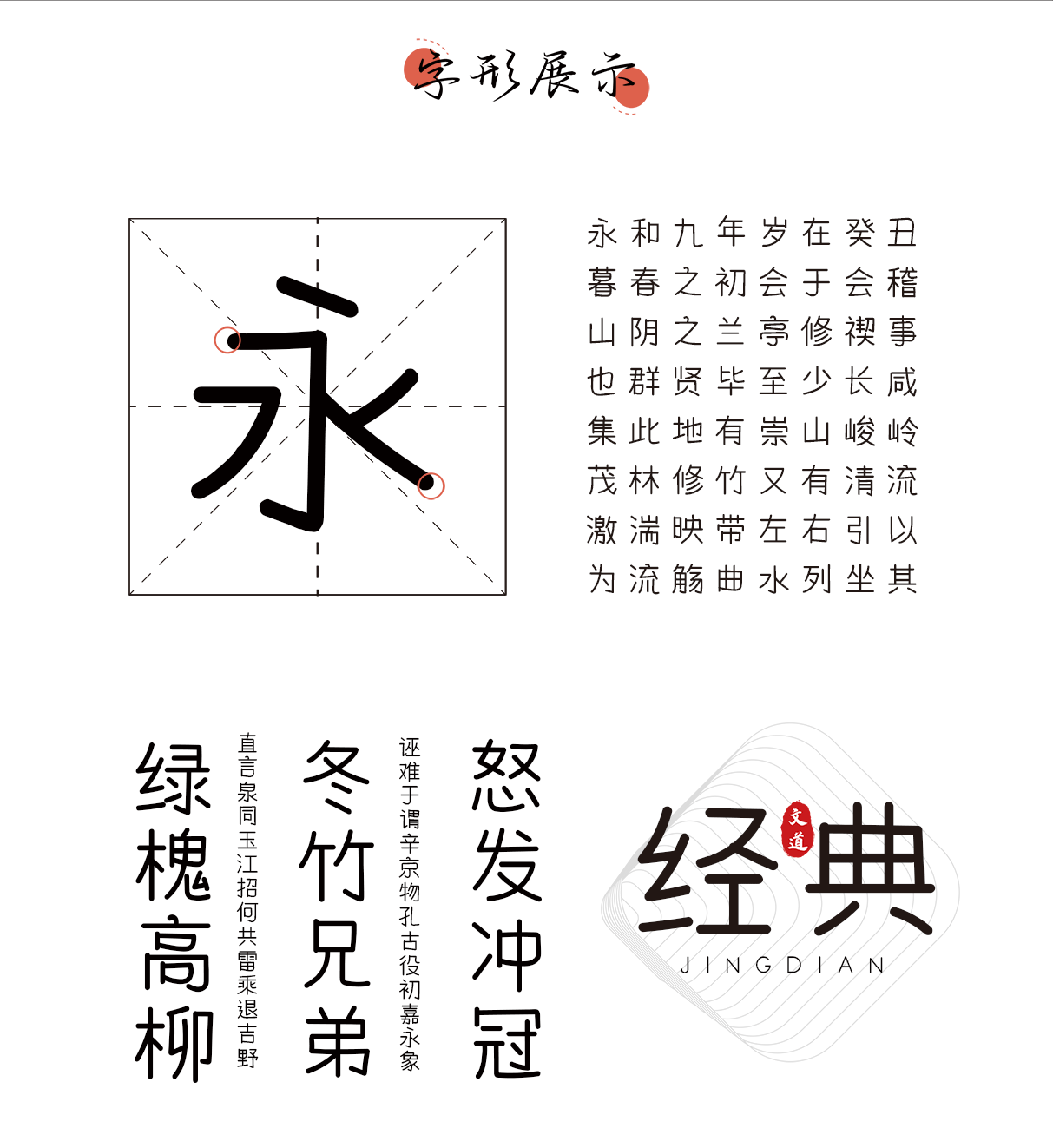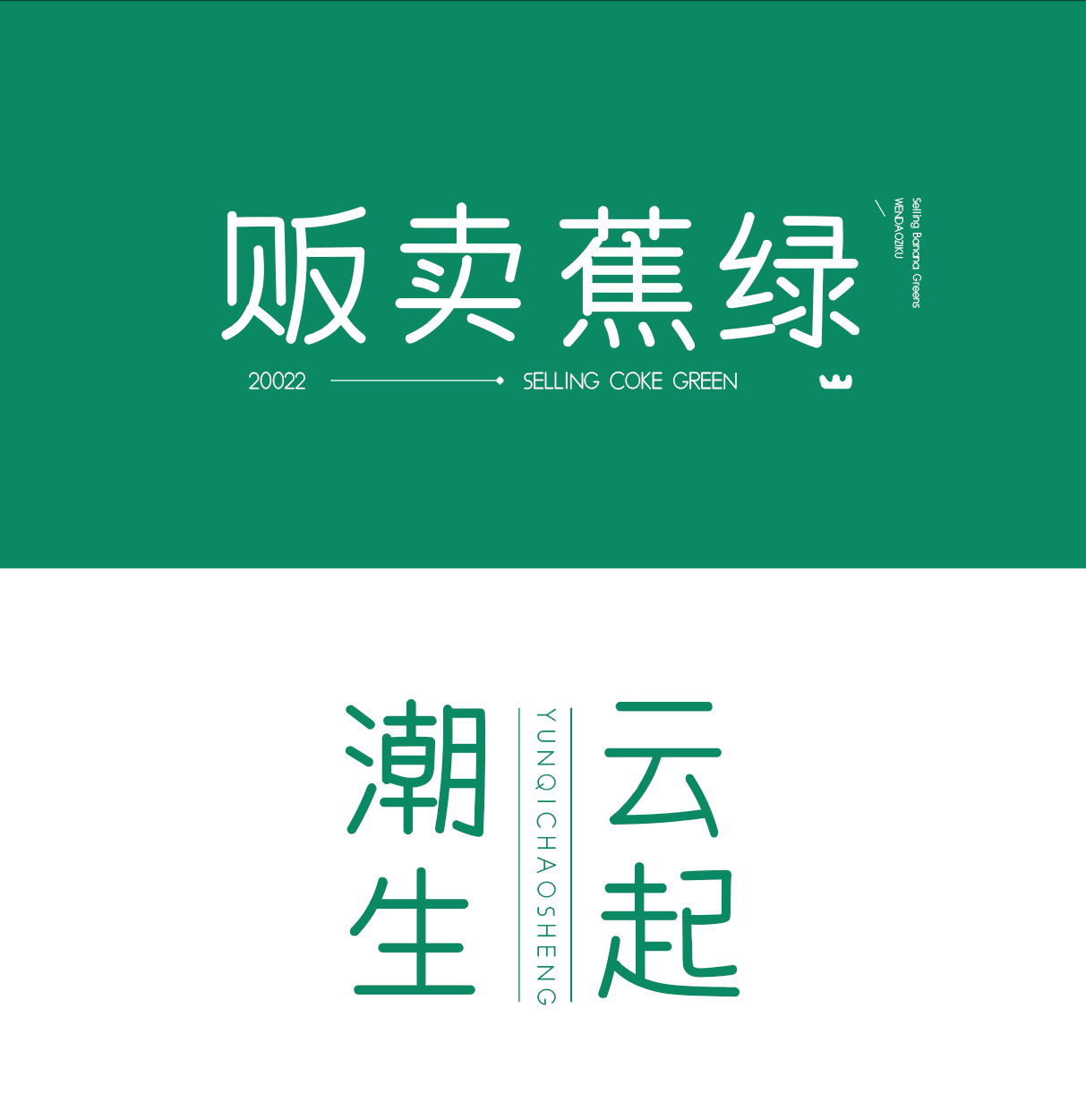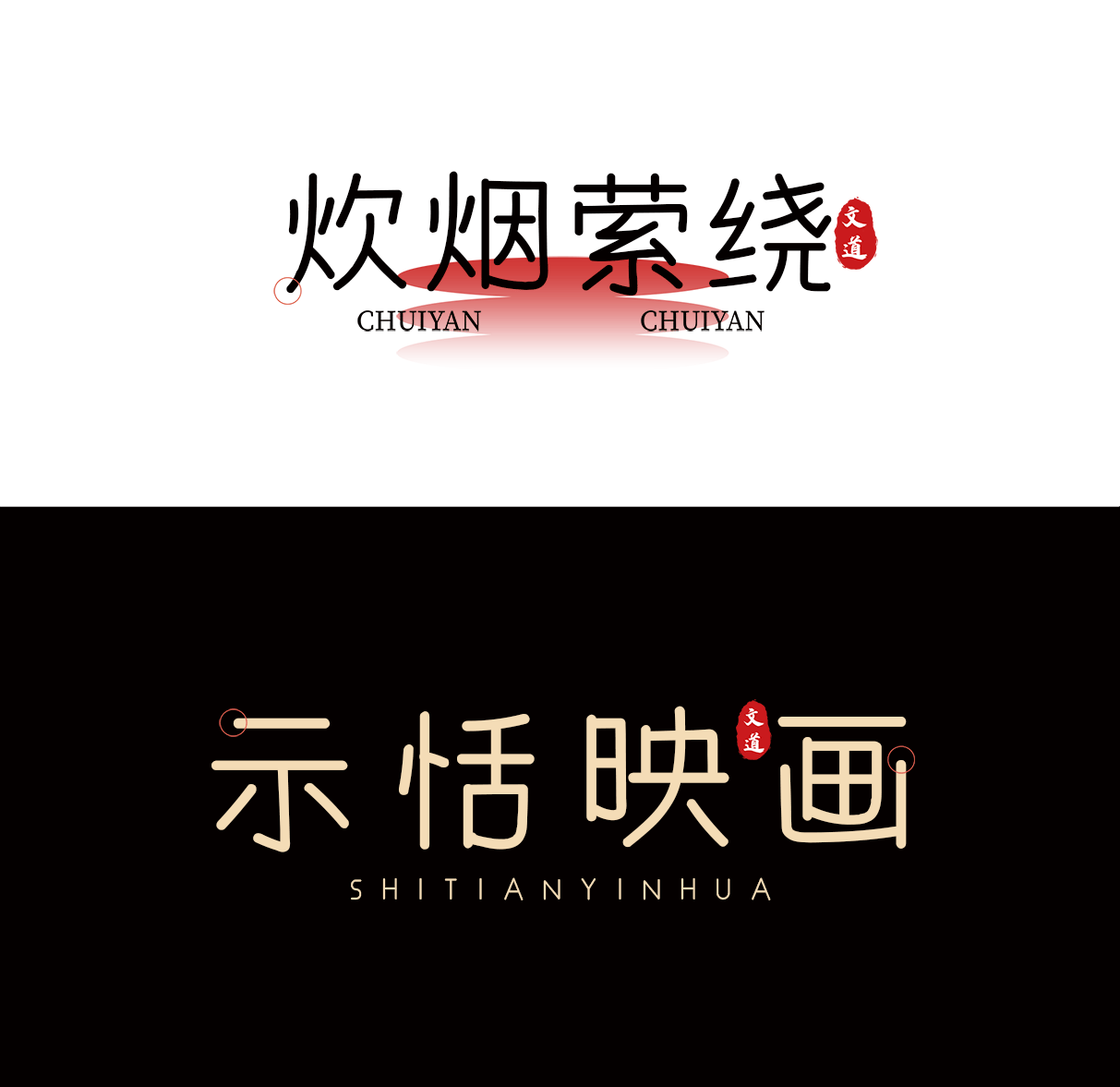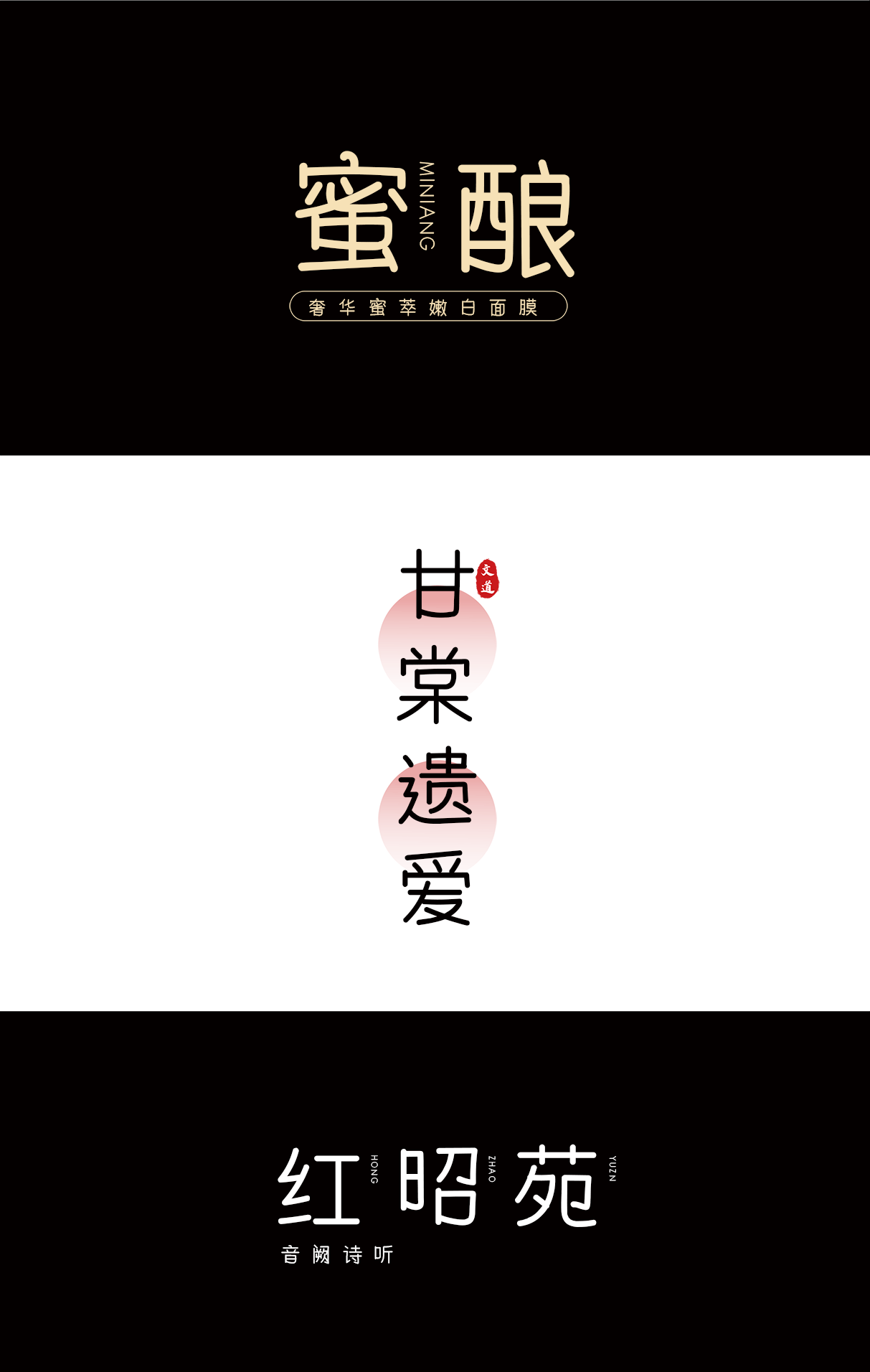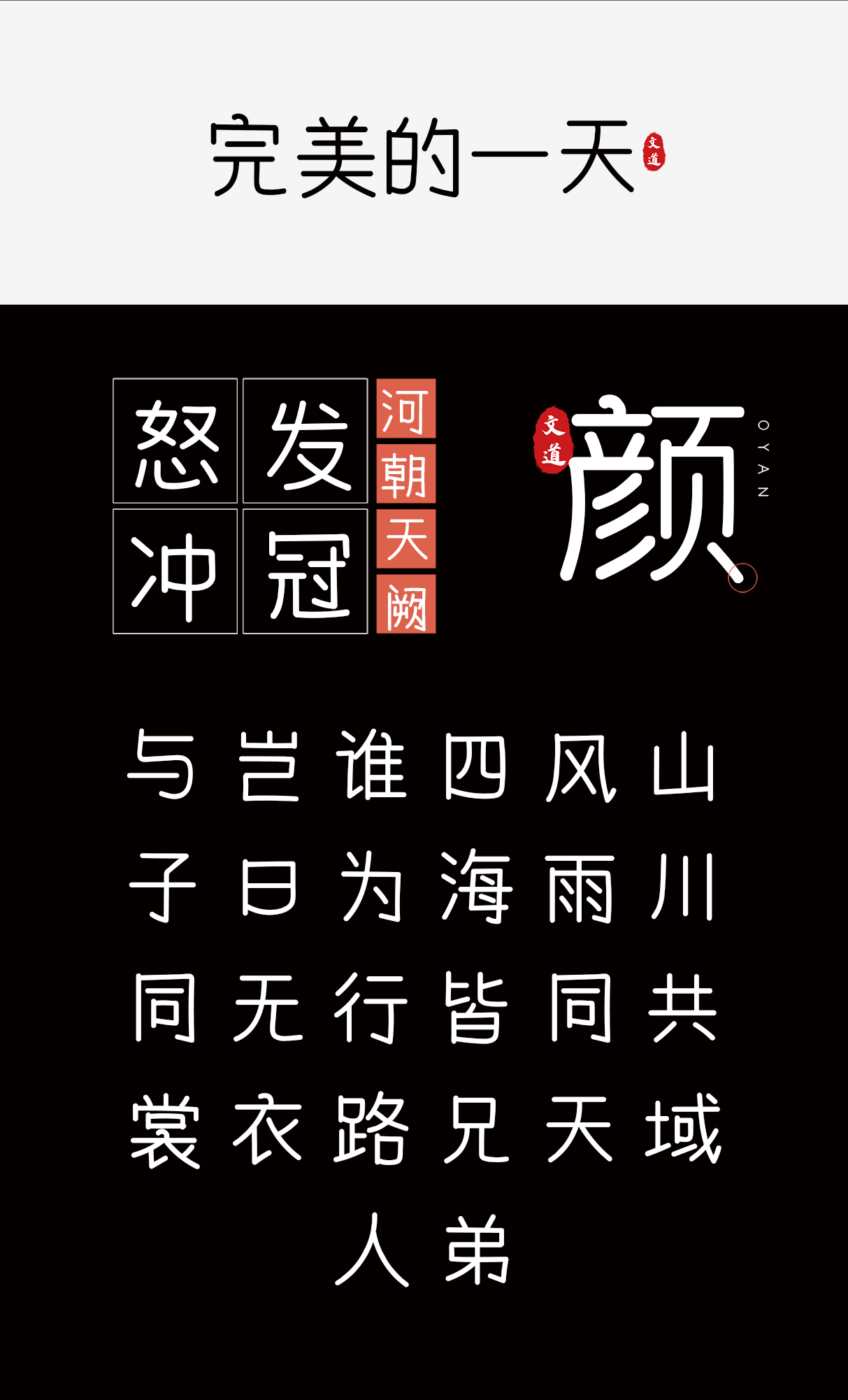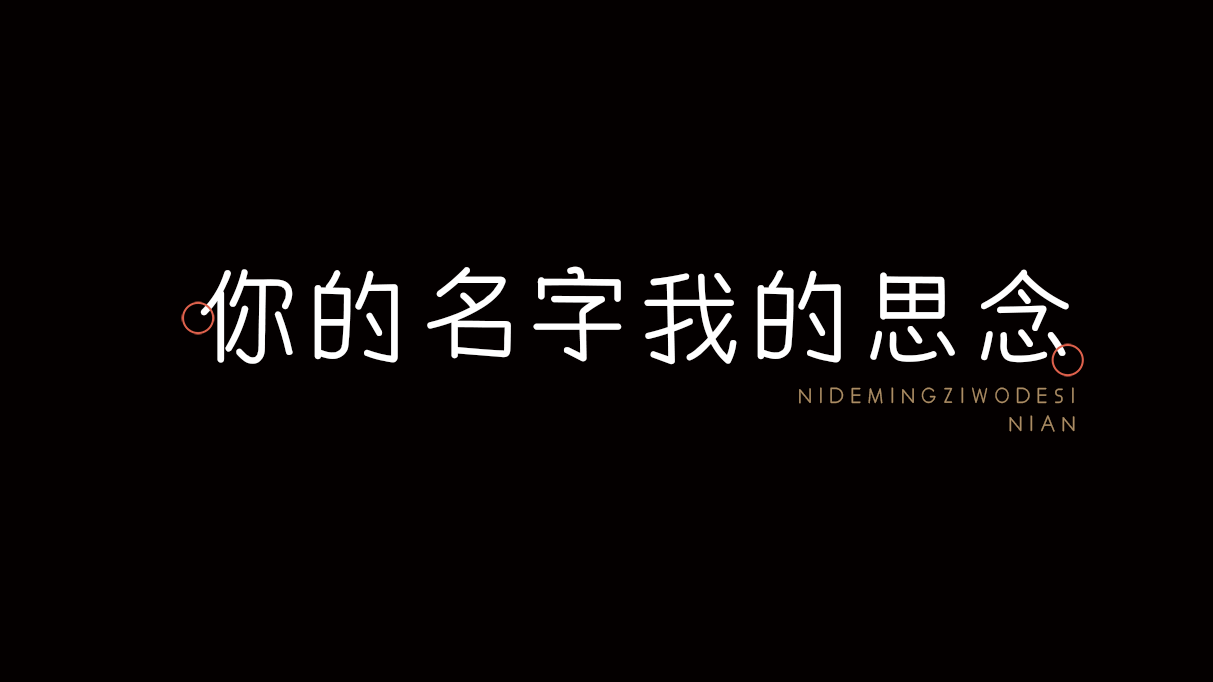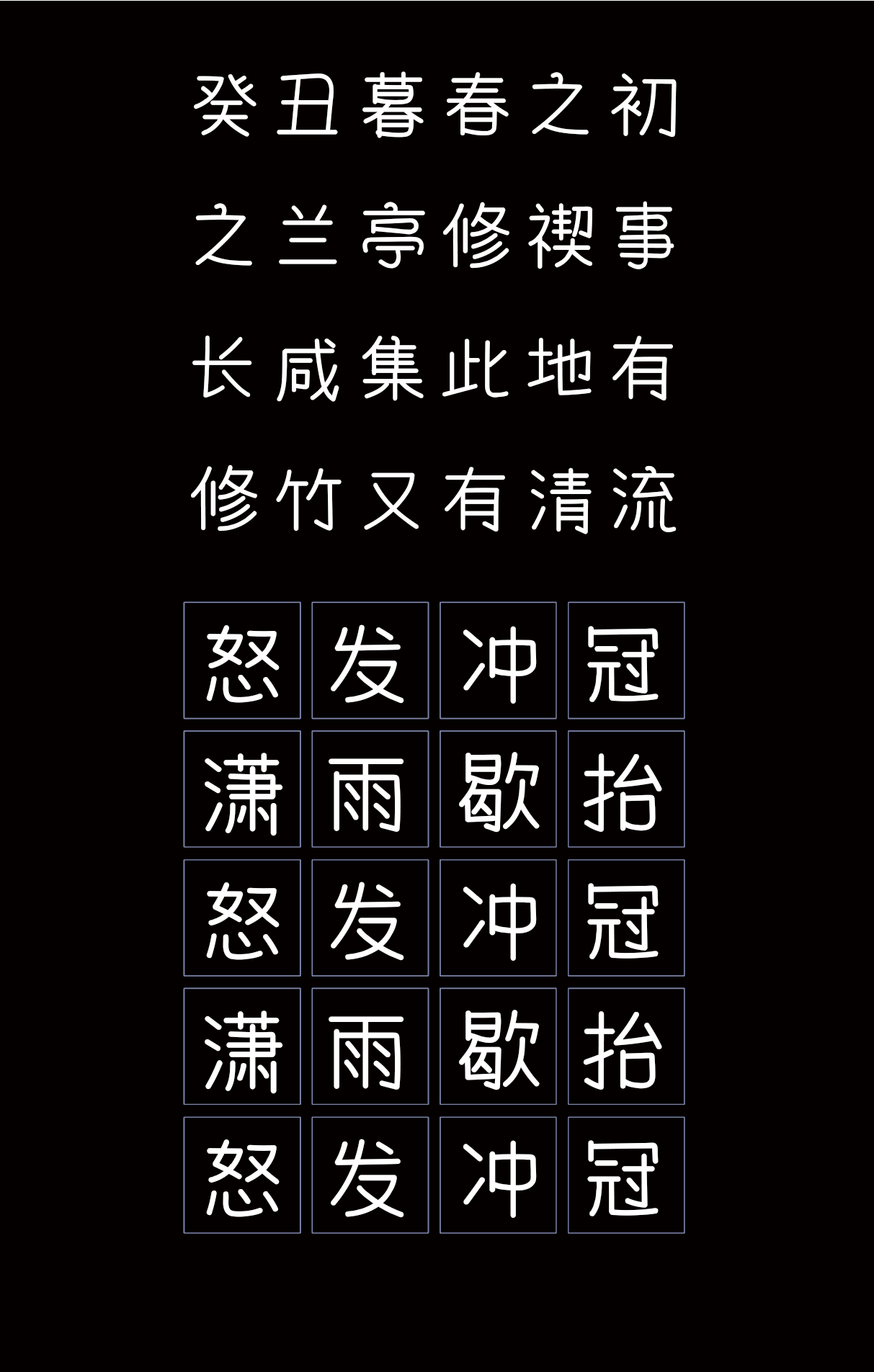
你的名字我的思念
文亦有道,笔墨添香;墨韵飞扬,意蕴绵长。
字体名称: 你的名字我的思念
简介: 【你的名字我的思念】是一种可商用创意字体,简约朴实的风格字体,带着静谧与沉着的微妙气质该字包含6763个中文、字母、符号和数字,令人舒适观赏性以及简约风格适合新媒体、电商、海报的标题和logo除了满足传统印刷媒介的标题,还适用于屏幕显示、短视频字幕和产品包装设计。